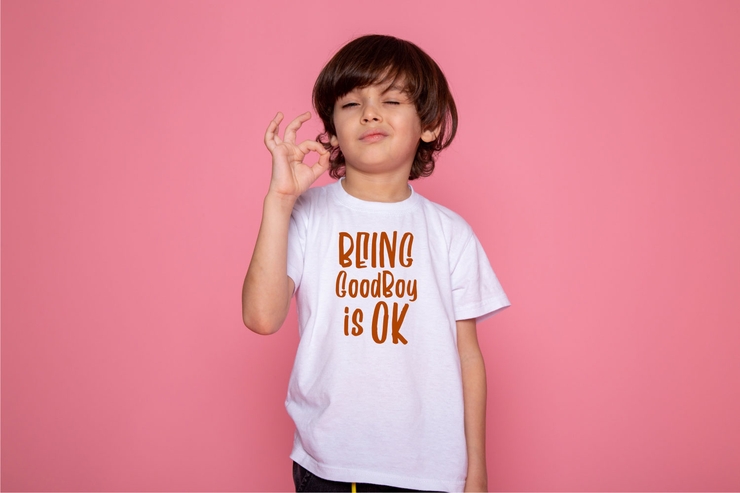
Funtalous Playful Stylish Modern Dekorative Englische Schrift
Funtalous ist eine lebendige und kreative dekorative englische Schrift mit sanften, verspielten Strichen und einzigartigen lässigen Glyphendetails. Ihr spaßorientiertes Design zeichnet sich durch freundliche Kurven und ausgewogene Strukturen aus und sorgt für eine fröhliche, jugendliche und entspannte visuelle Atmosphäre. Diese vielseitige Schrift ist ideal für Designs mit Kindermotiven, Social-Media-Posts, Partyposter, Markenlogos, Verpackungsetiketten, Webbanner und lässige grafische Kreationen. Komplett mit Groß- und Kleinbuchstaben ist sie vollständig skalierbar und lässt sich leicht an Farben, Größen und Layouts anpassen, während sie ihre unverwechselbare spaßige Textur beibehält. Geeignet für Grafikdesigner, Inhaltsersteller und kommerzielle Projekte, um verschiedenen visuellen works.Free für den kommerziellen Gebrauch eine lebendige, lebendige Persönlichkeit zu verleihen / Kein Copyright 1